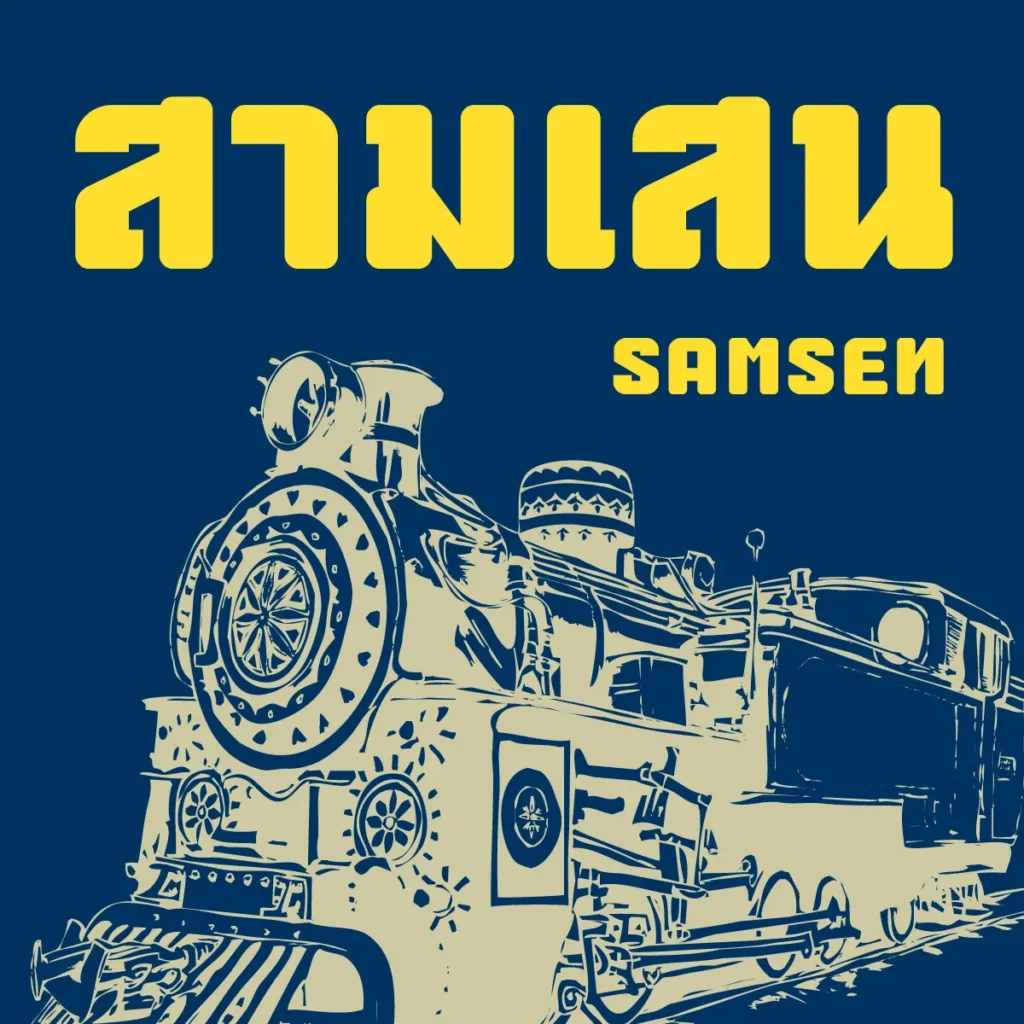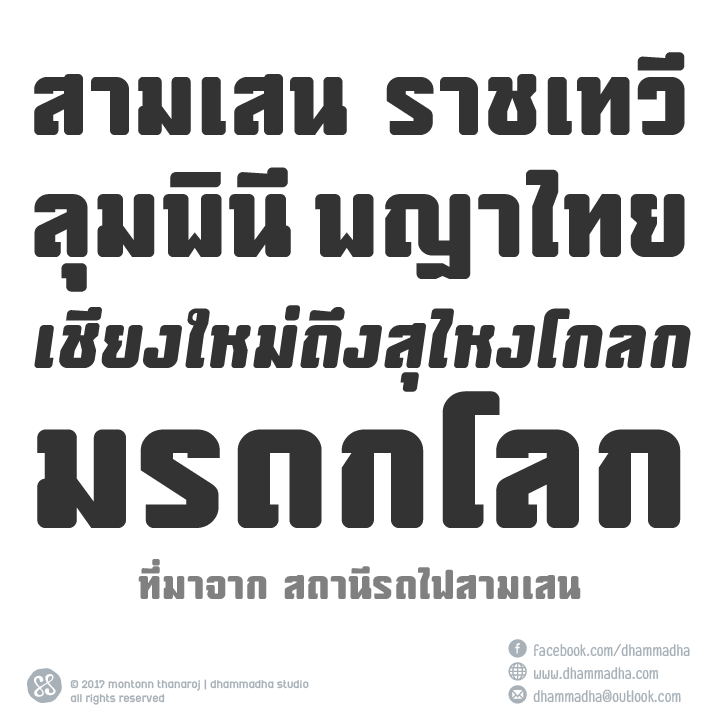
samsen เป็นชุดอักษรที่ได้แรงบันดาลใจจากป้ายสถานีรถไฟสามเสน ตอนที่ขีดๆ เขียนๆ ลงในสมุดจด เป็นวันที่เดินทางกลับจากงาน TFACE#2 ถือว่าเป็นงานอักษรแรกๆ ที่ลองทำเลย แต่ไปๆ มาๆ ก็ยังไม่ได้เอามาทำให้เสร็จสมบูรณ์สักที
samsen ยังคงรูปลักษณ์เดิมของป้ายต้นแบบไว้ และเพิ่มเติมปรับแต่งให้เหมาะสมกับการใช้งาน โดยยึดแนวคิดไว้ที่ การคงรูปแบบเก่าไว้ และเพิ่มความร่วมสมัยลงไปอีกหน่อย